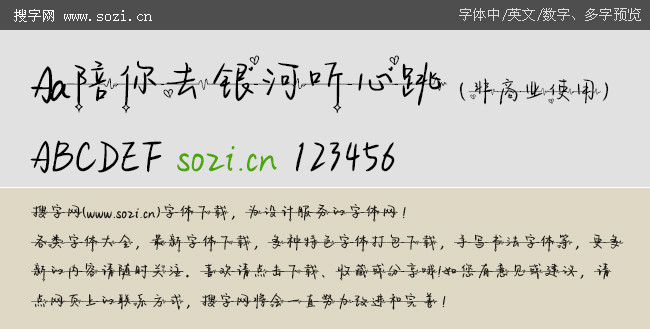
Aa陪你去銀河聽心跳
搜字網(wǎng)給大家提供一款A(yù)a陪你去銀河聽心跳(非商業(yè)使用)中文字體下載,該字體是一款手寫風(fēng)格的卡通字體,字體字體筆觸適中,書寫流暢,在字體的中間有一條心動(dòng)的波浪線,增加了趣味性。適用于平面宣傳設(shè)計(jì)、網(wǎng)頁設(shè)計(jì)、海報(bào)設(shè)計(jì)等應(yīng)用(此字體為個(gè)人非商用版,商用可以聯(lián)系QQ:1006760504)。